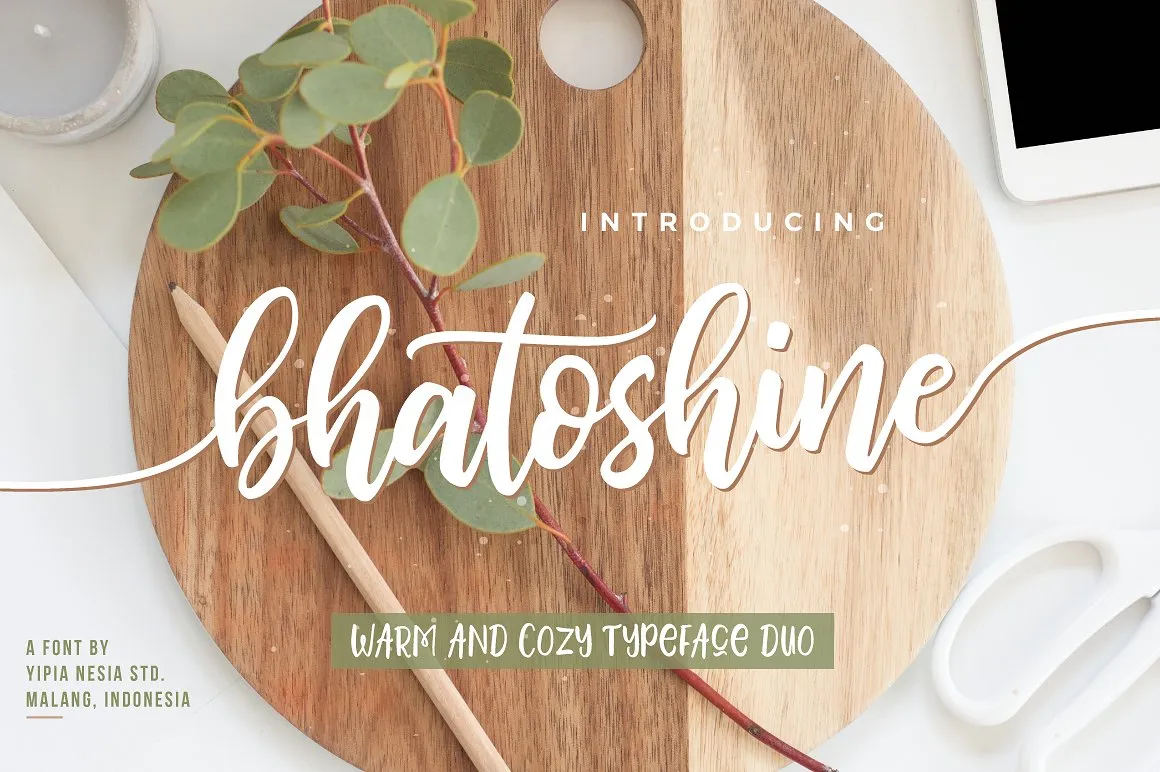
Bhatoshine Script Font – Download Grátis
Introduzimos Bhatoshine Script Font! Desenhada por Typia Nesia, esta é uma fonte premium que você pode encontrar na Crêativemarket. Atualmente está disponível gratuitamente para download. Este duo de tipos chamado Bhatoshine Fancy Font Duo apresenta duas versões do mesmo conjunto de caracteres: Regular e Caps. As versões de cada tipo são criadas através de um processo de pintura à mão, resultando em uma textura suave e carinhosa que traz consigo elementos divertidos. Este dueto de tipos permite criar qualquer palavra com unidade única, o que transforma as letras em belas tipografias. A Bhatoshine Regular é perfeitamente combinável com a versão Caps, resultando em um design único para cada palavra escrita com essas duas fontes juntas. Sua designação pode incluir qualquer tipo de necessidade, desde designs modernos para convites até marca e decoração de estúdio. Os Bhatoshine Fancy Font Duo também são ideais para blogs, marketing moderno, design de convite, decoração artística de citações, títulos de livros/capa, eventos especiais, desejos de aniversário, talheres personalizados, almofadas e camisetas. Além disso, se você estiver procurando por qualquer tipo de escrita à mão com pincel, este é um excelente conjunto para escolher.